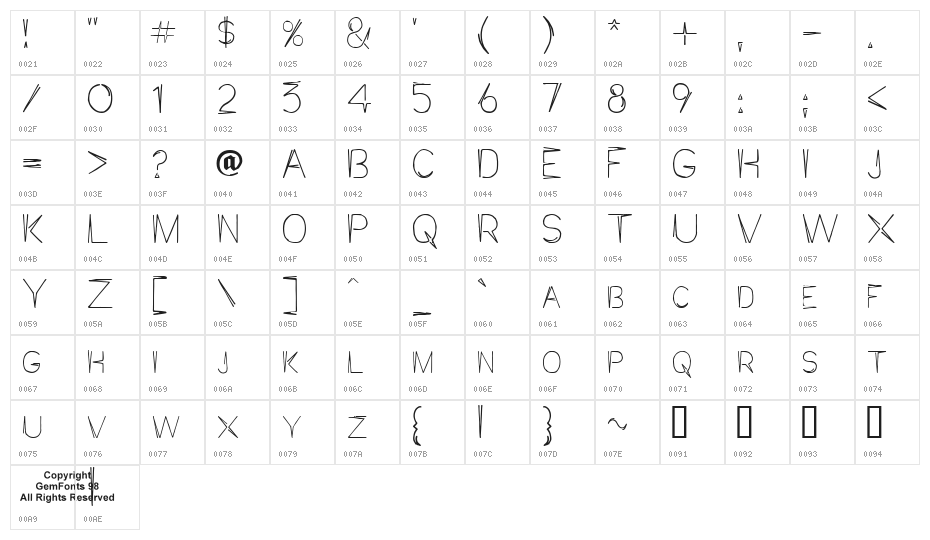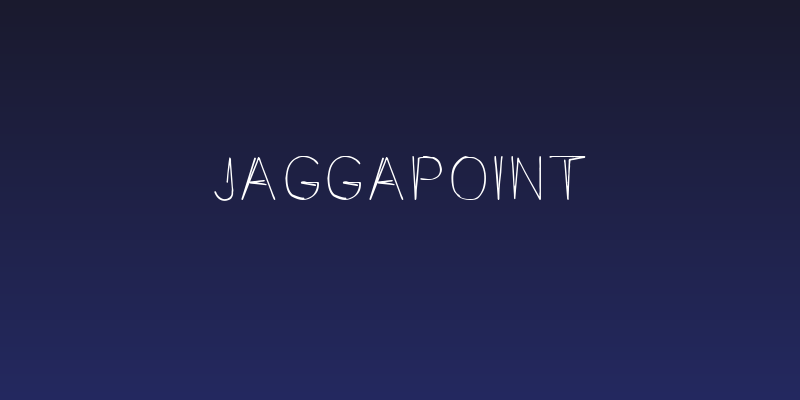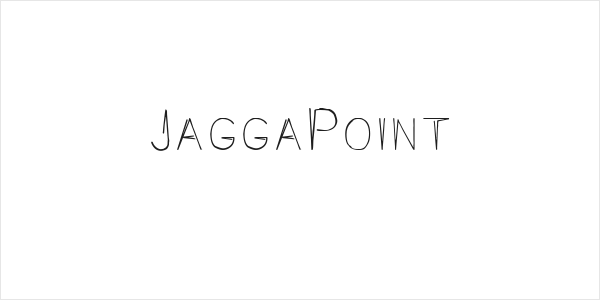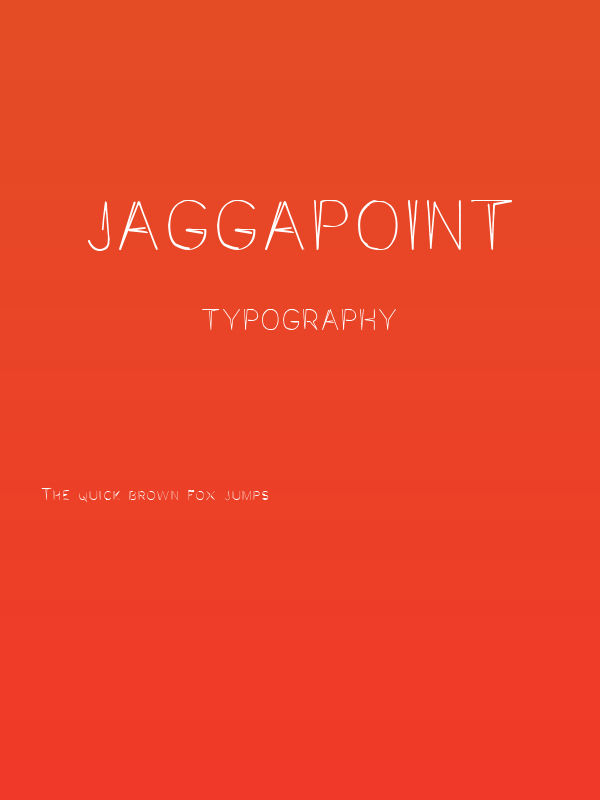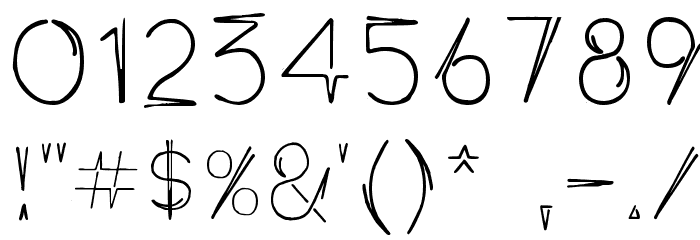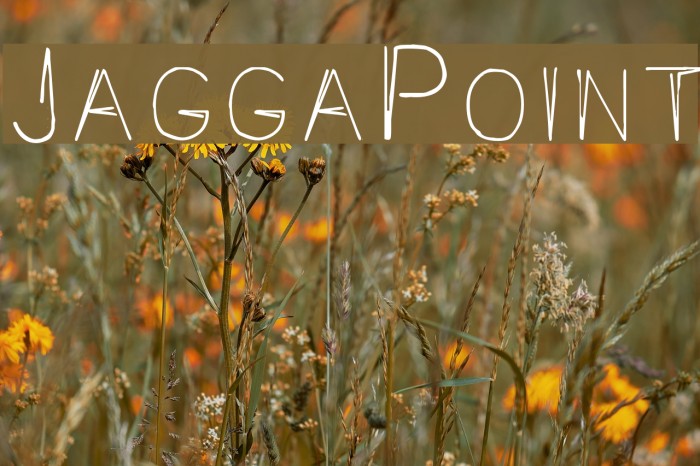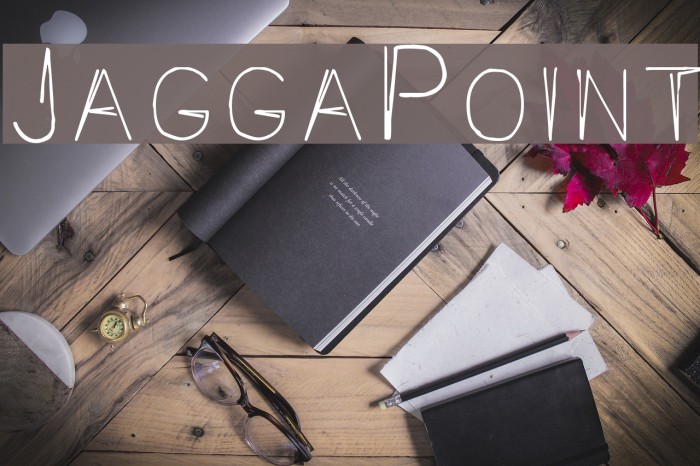
JaggaPoint Font
Fonts by Graham Meade - GemFonts
| Stile generale | Artistic, Whimsical |
| Progetti proposti | Ideal for artistic posters, creative branding, children's books, and unique invitations. |